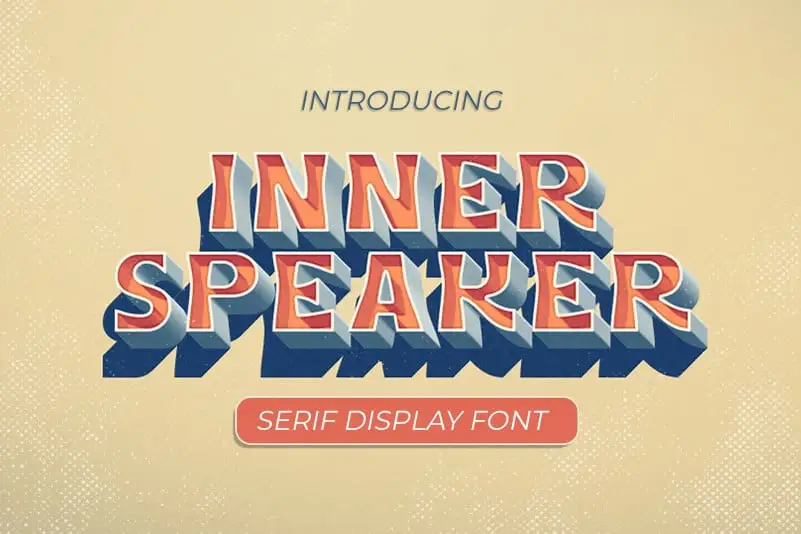
A Innerspeaker Display Font é uma escolha ideal para aqueles que procuram uma fonte séria e moderna para seus projetos de texto breve ou título. Ela foi criada principalmente para headlines e outras seções curta-texto, oferecendo um equilíbrio entre simplicidade e beleza. Este estilo é inspirado em serifos antigos, mas a Innerspeaker Display traz uma aparência elegante e única, com um toque moderno que combina bem em qualquer projeto visual. A fonte é ideal para criar um design impecável em sua próxima campanha de marketing ou site corporativo. Se você está procurando por uma alternativa à serifos mais tradicionais que ainda mantém a elegância e o encanto das fontes antigas, então a Innerspeaker Display Font é definitivamente a escolha certa. Com a sensação vintage do tipo antigo e a simplicidade da sua estrutura sem serifas, a Innerspeaker Display oferece um estilo que se destaca em qualquer ambiente de design. Se você estiver buscando uma fonte moderna para seus projetos de texto curto ou seu próximo trabalho gráfico, considere experimentar a Innerspeaker Display Font. Esse é o tipo certo para capturar os olhos do seu público e destacar sua mensagem com clareza e elegância.